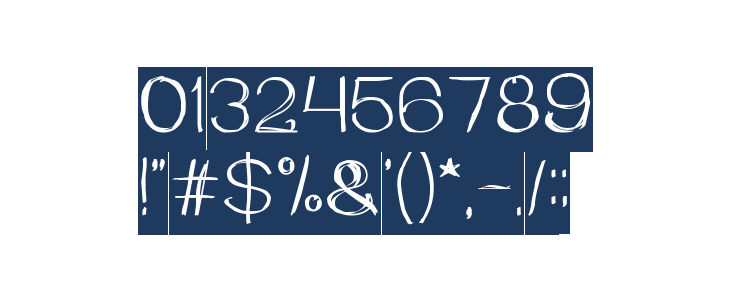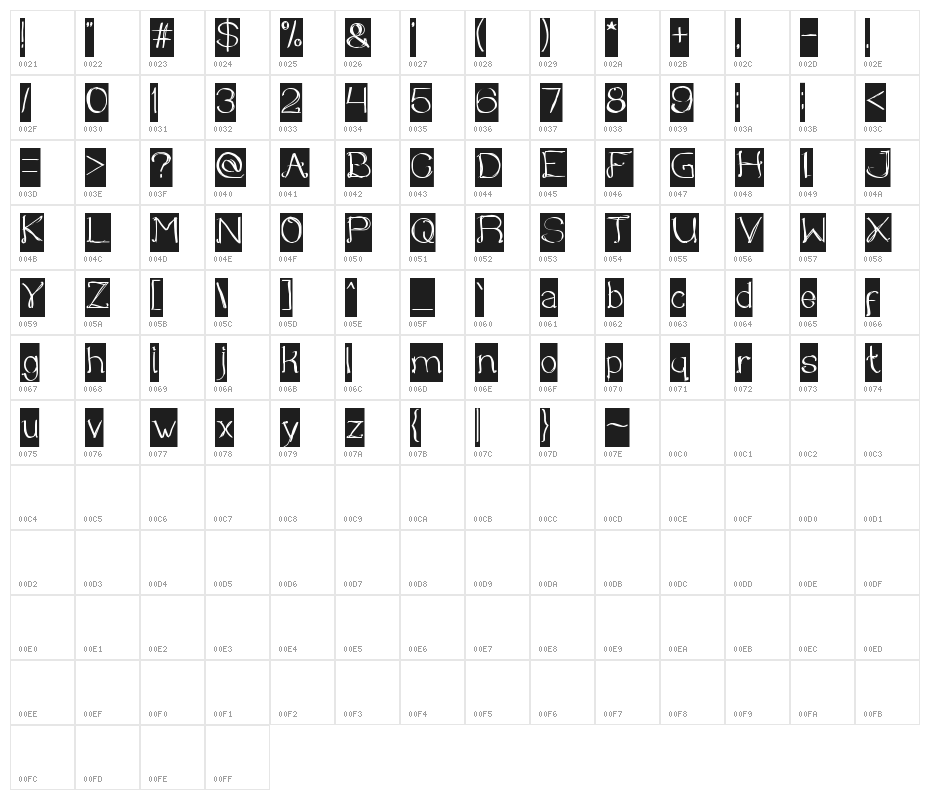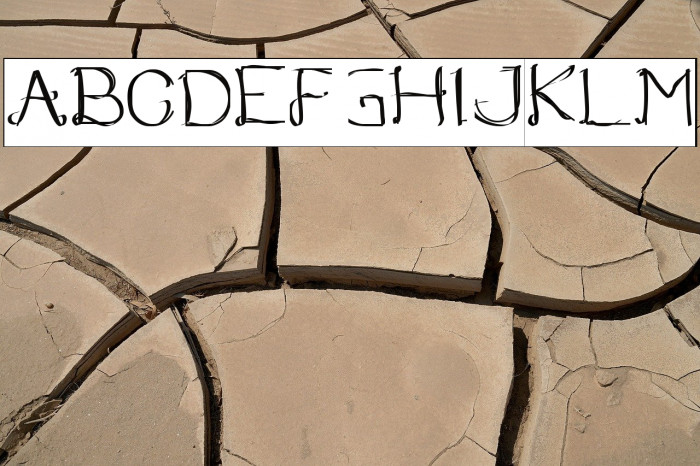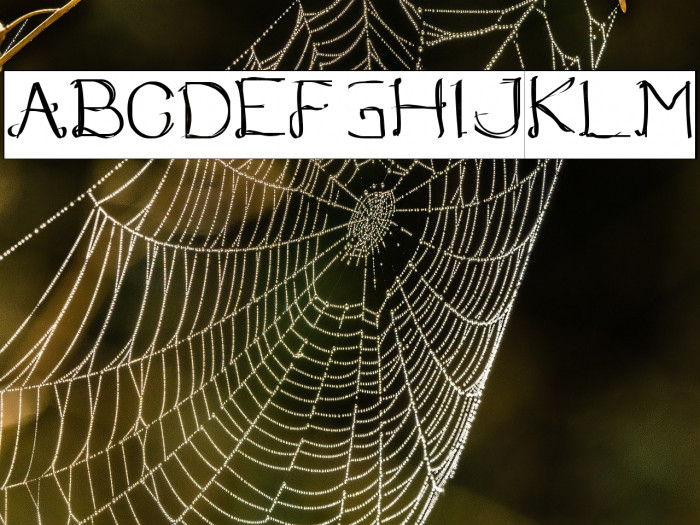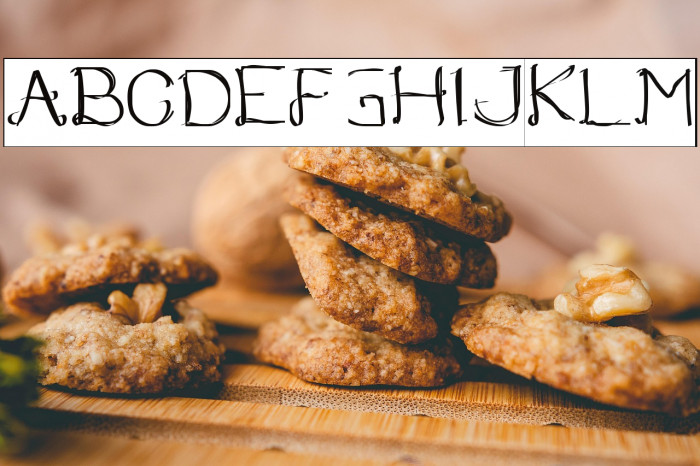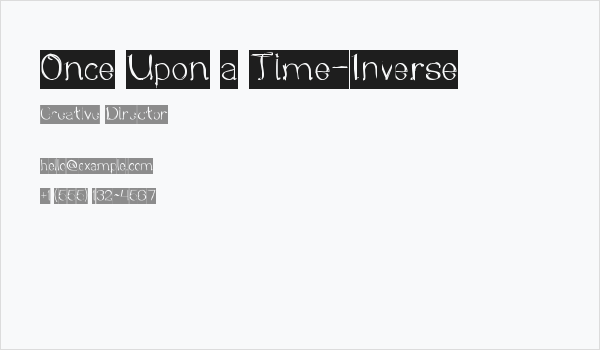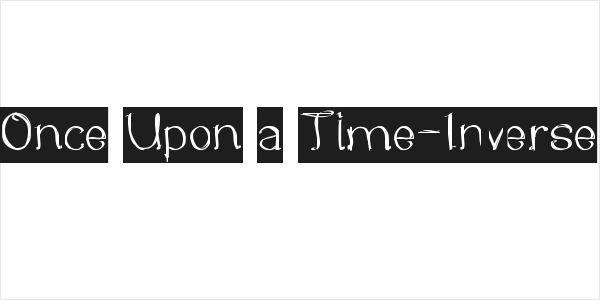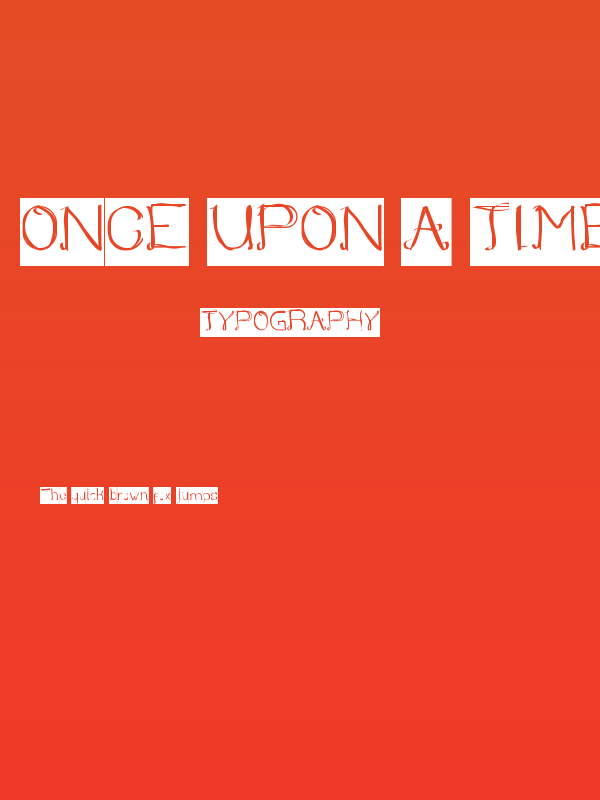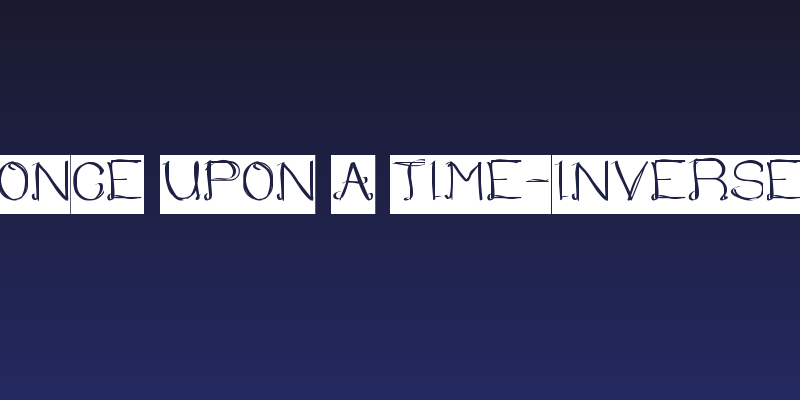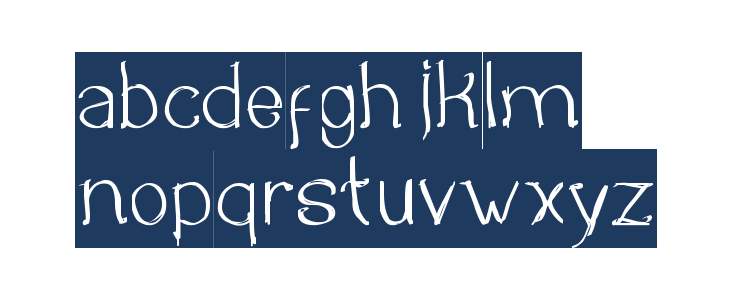
Once Upon a Time-Inverse Font
| Stile generale | Whimsical, Playful |
| Caso d'uso | Headlines, Logos, Invitations |
| Progetti proposti | Ideal for children's books, fantasy-themed designs, invitations, and playful branding. |